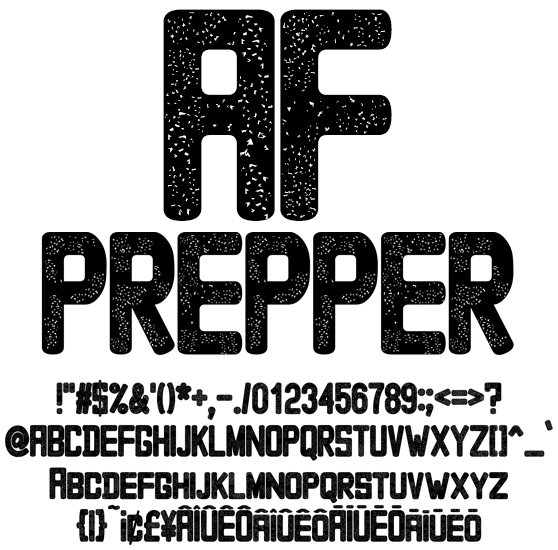
クラック欧文フォント AFPREPPER
AFPREPPER
文字内側に経年劣化をイメージしたデザインを施しました。個人同人向けのアニメ/動画/ドキュメント表紙などの大見出し用です。記号類、マクロンやサーカムフレックスなどのダイアクリティカルマーク追加と強めのカーニング。日本のローマ字表記で使われる訓令式やヘボン式で扱うÔやŌを収録しました。小文字は大文字デザインのスモールキャップス。